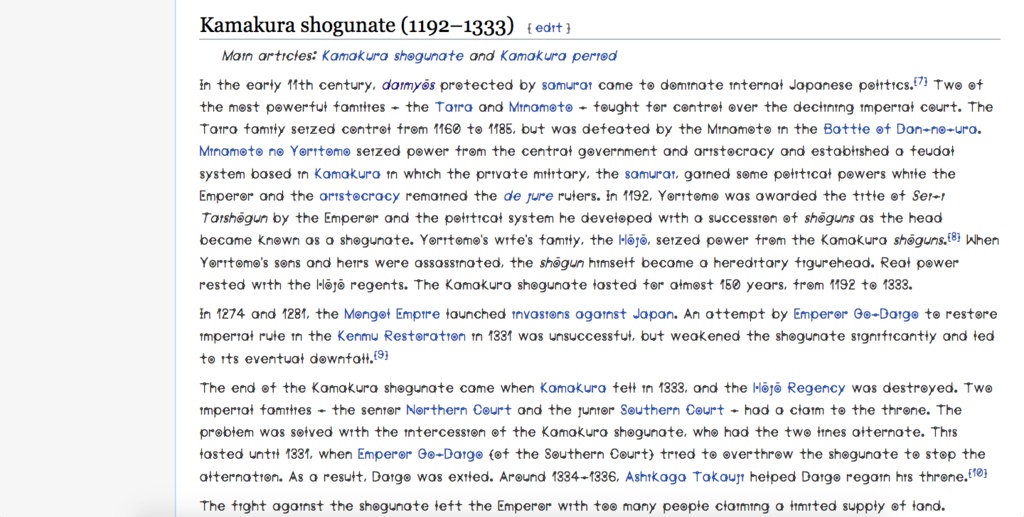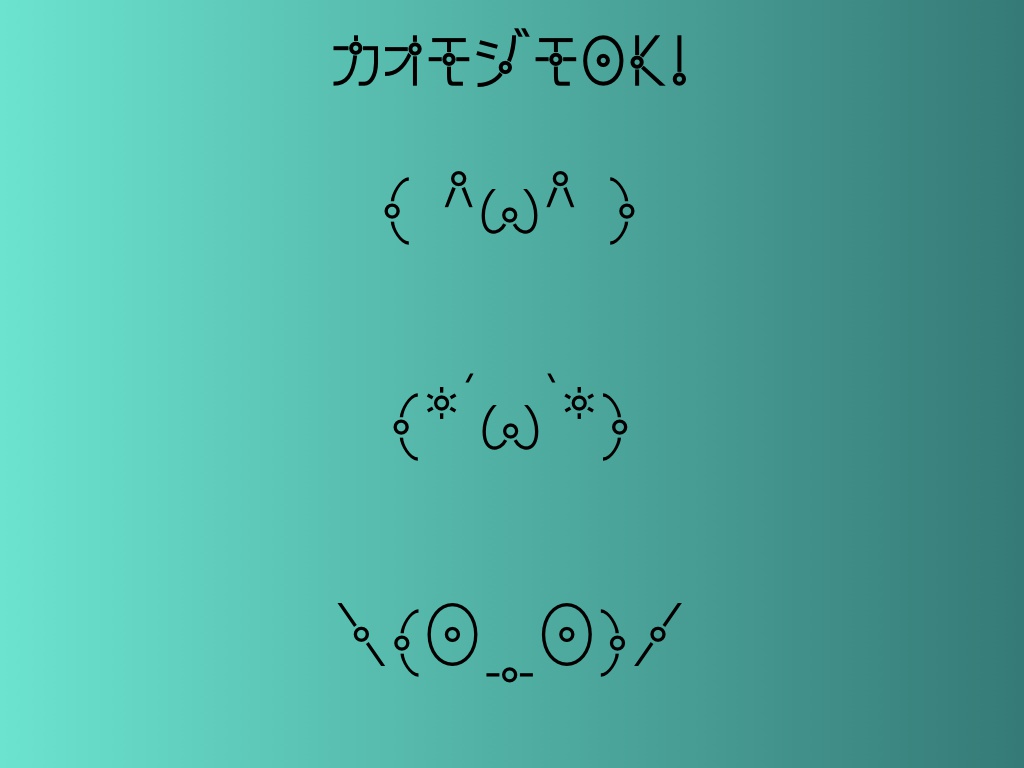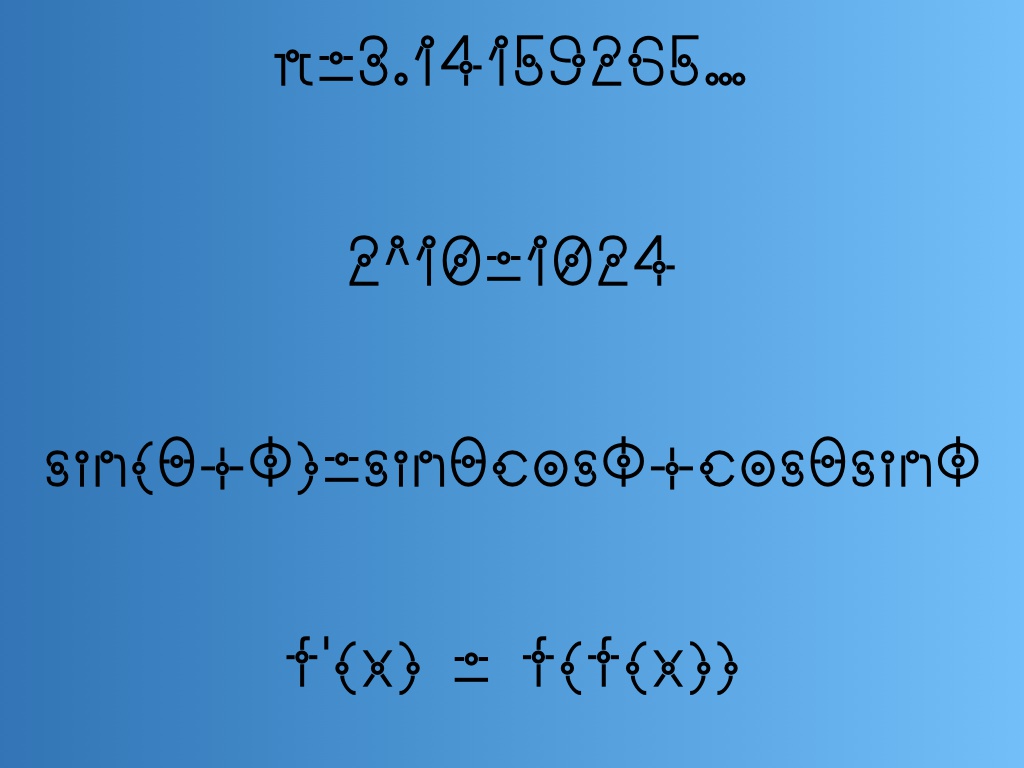
欧文/カタカナフォント CORORIN
マルを用いたかわいいフォントCORORIN、コロコロとした見た目です。可読性が高く、地の文として用いても問題なく読むことができます。 レギュラーとボールド両方を同封していますので、ダウンロードしてご利用ください。 印刷はもちろん、商用利用もOKです! カタカナの他、アクセント付き文字なども含め、ラテン文字、ギリシャ文字、キリル文字を収録。 これにより ・英語 ・日本語(カタカナ) ・フランス語 ・ギリシャ語 ・ロシア語 ・スペイン語 ・ドイツ語 などをこのフォントで表示することができます! フォントのバージョンアップのお知らせはこちらで投稿します。フォローお願いします🙏 https://www.pixiv.net/fanbox/creator/31276656